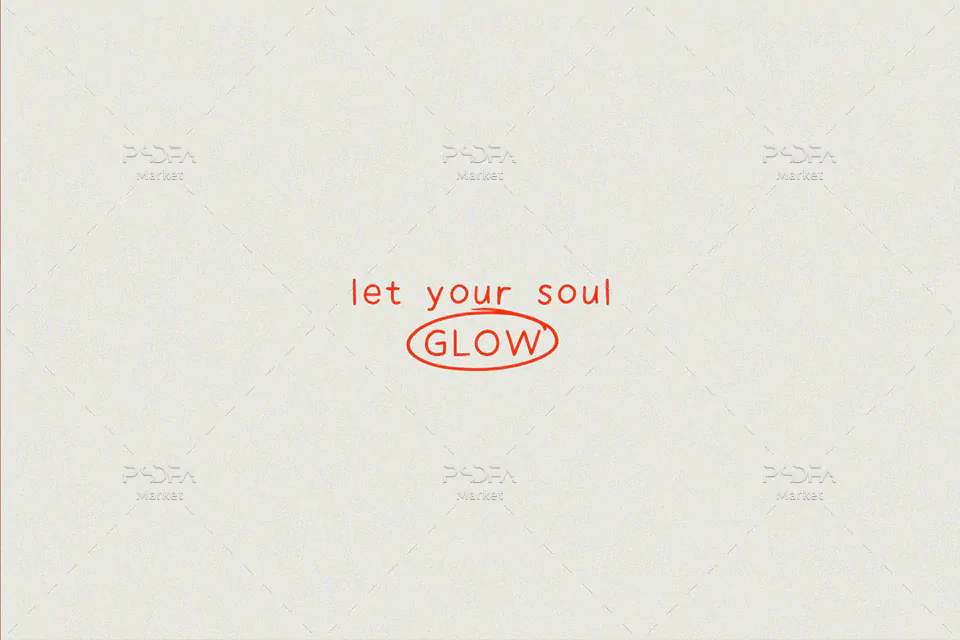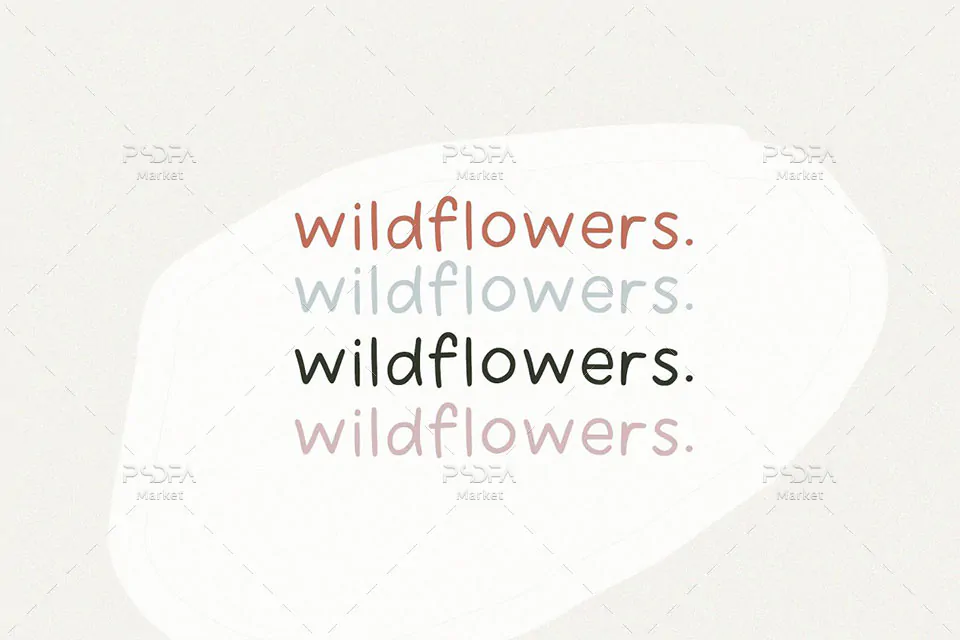
فونت دستنویس و تحریری انگلیسی Wildflower به همراه فونت سمبل
فونت دستنویس و تحریری انگلیسی Wildflower
فونت دستنویس و تحریری انگلیسی Wildflower به همراه فونت سمبل مجموعهای از 2 قلم فوق العاده زیبا است که مناسب جهت استفاده در طرحهای گرافیکی مختلف به خصوص طراحی انواع لیبل و برچسب بسته بندی محصولات و … میباشند. این 2 فونت زیبا در قالب 5 فایل OTF, TTF, WOFF در فایل محصول قرار دارد که با نصب یکی از 2 فرمت ttf یا otf در پوشه فونتهای سیستم میتوانید از این فونت انگلیسی در تمام نرم افزارهای گرافیکی و تایپ متون همچون فتوشاپ، افتر افکت، پریمیر، ورد، پاورپوینت و … استفاده کنید.
فونت Wildflower در وزن معمولی (Regular) طراحی شده است که میتوانید از آن در طراحی انواع کارت تبریک، کارت پستال، بسته بندی محصولات، طراحی لوگو، کاور آلبوم موزیک، طراحی انواع بنر، پوستر، تراکت، تقویم و دیگر طرحهای گرافیکی استفاده کنید. از نسخه woff این قلم نیز میتوانید در طراحی صفحات وب استفاده کنید.